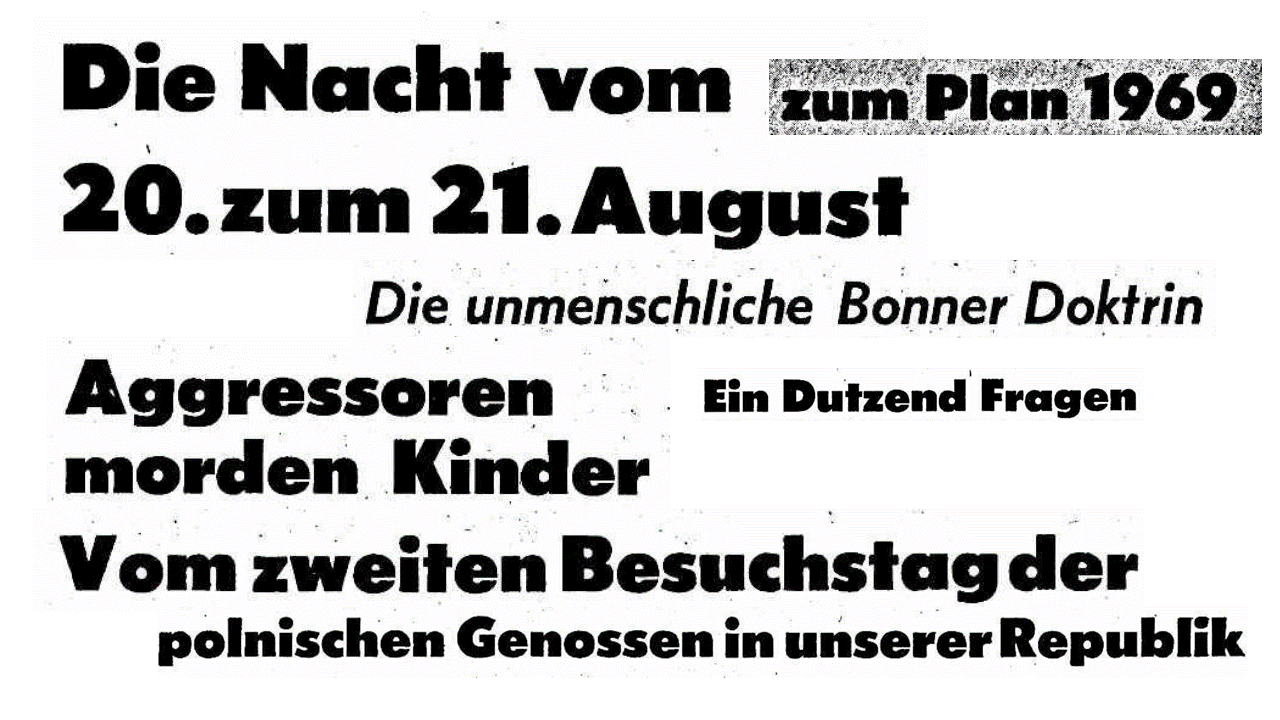
Schriftart Neues Deutschland in den 1960ern
Neues Deutschland (DDR-Tageszeitung)
Ich habe mich bei der Jungen Welt und dem ND immer gewundert, dass die, neben der Super, gleichzeitig eine "Art" Futura verwendet haben. Ich bin mir aber fast sicher, dass es sich nicht um die klassische Version der Futura handelt. Meines Erachtens gab es von der fetten Version auch eine kursive - habe sie aber leider nicht gefunden.
Kann mir jemand helfen, welche Futura-ähnliche Schrift das ND verwendete? Lieben Dank.